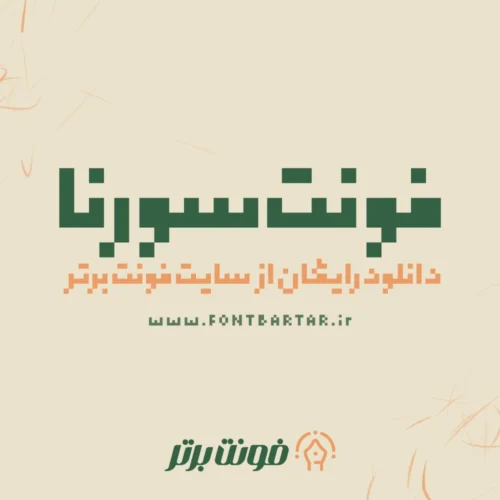
فونت زیبا سورنا
سورنا یک تایپ‌فیس پیکسلی انگلیسی-فارسی است. بهترین فونت زیبا پیکسلی در کوچک ترین اندازۀ پیکسلی طراحی و ساخته شده است. از چالش های طراحی فونت زیبا سورنا، حذف جزئیات در کنار وجود خوانایی بود.
نحوۀ استفاده از فونت زیبا فارسی سورنا در آرت های پیکسلی:
فونت فارسی سورنا را فارغ از هر نرم‌افزاری برای طراحی، می‌توان استفاده کرد.
فونت زیبا رایگان اندازهٔ سورنا Pixel باید ضریبی از ۶.۴ و اندازهٔ سورنا Normal ضریبی از ۲۵.۶ باشد تا فونت به طور صحیح در آرت پیکسلی مورد استفاده قرار گیرد.
نکتهٔ قابل توجه این است که فونت تایپوگرافی سورنا چون یک فونت پیکسلی است نیاز به حالت smooth یا رندر های anti-aliasing نیاز ندارد و فعال بودن این ویژگی ها سبب رندر اشتباه فونت سورنا می‌شود.
فونت پیکسلی سورنا از چه زبان هایی پشتیبانی می‌کند؟